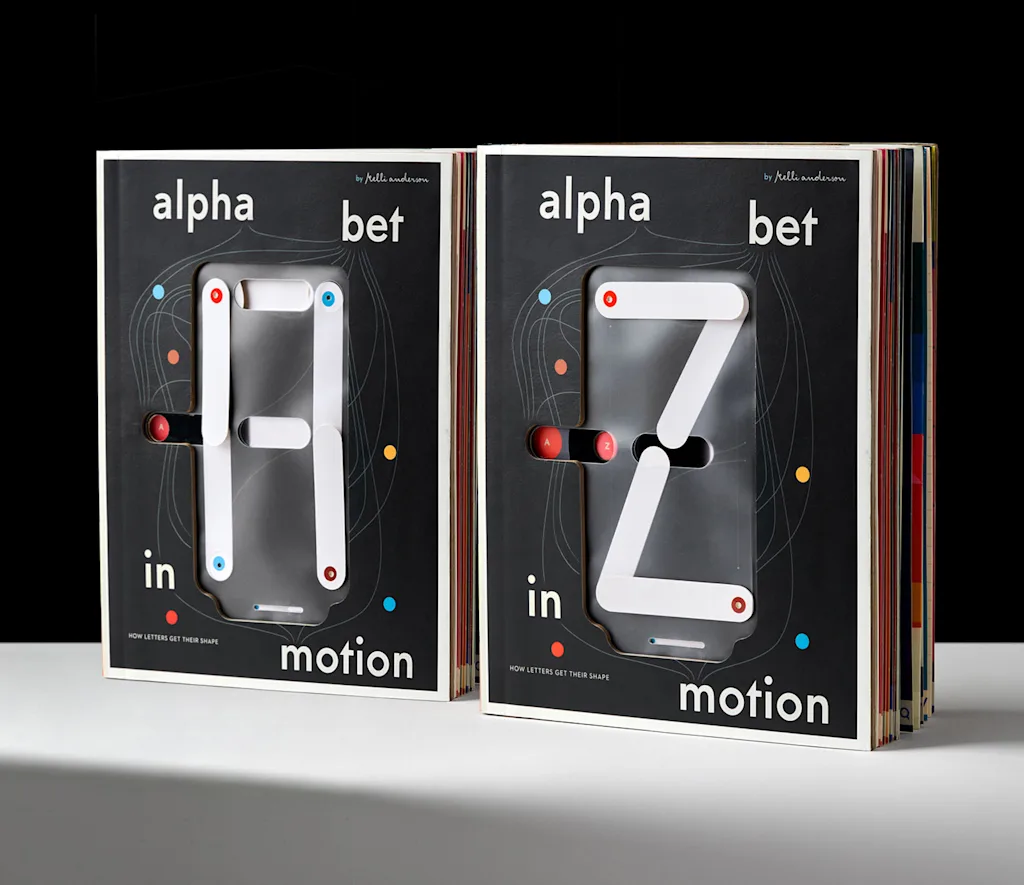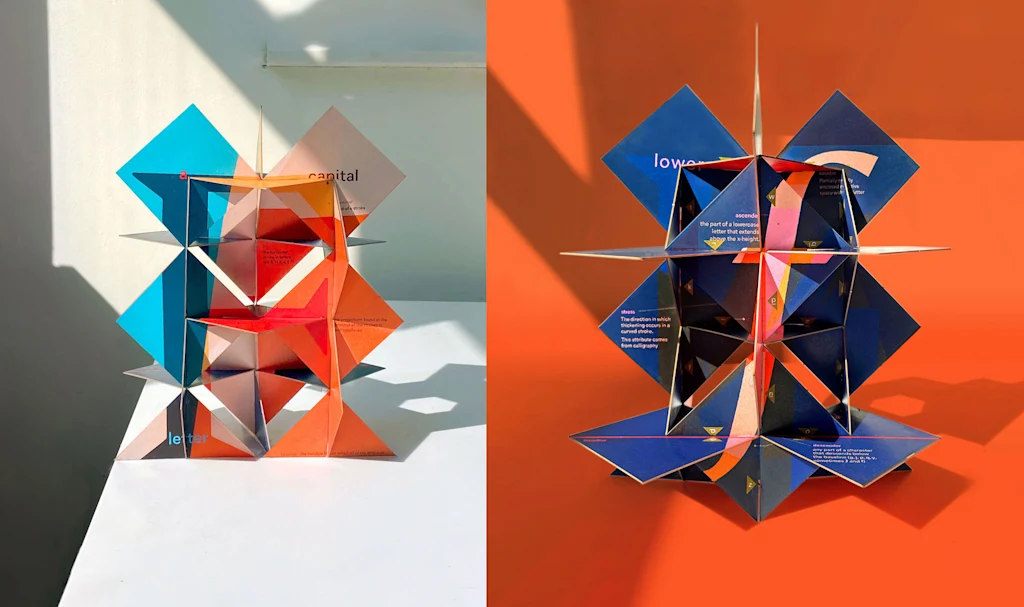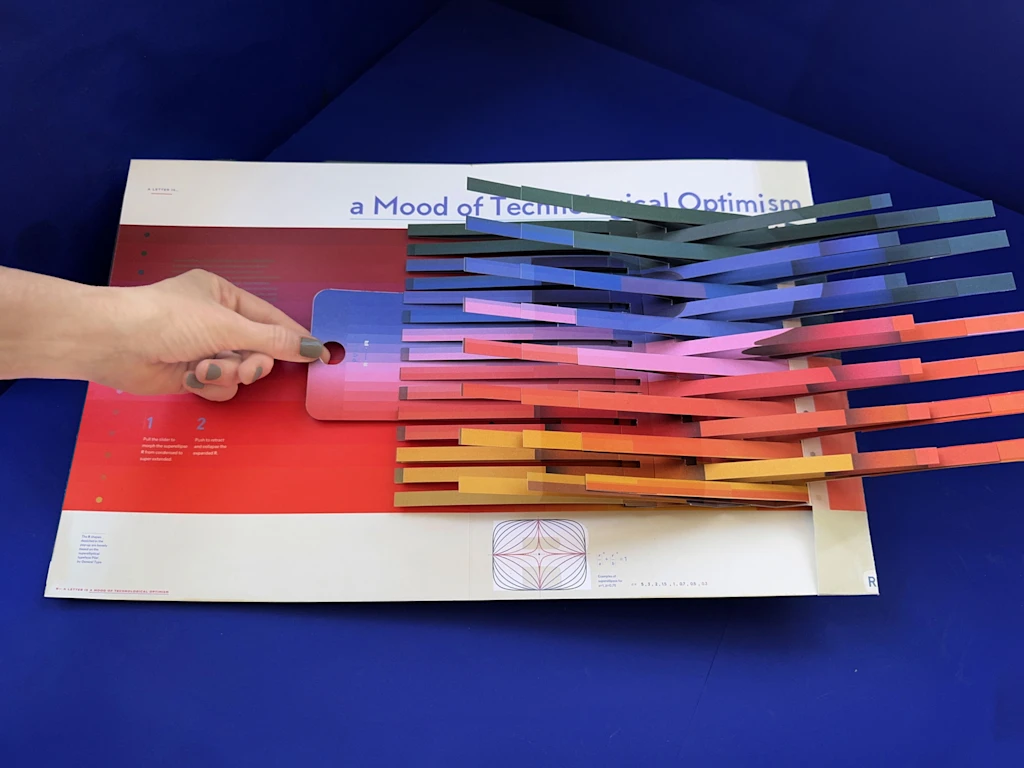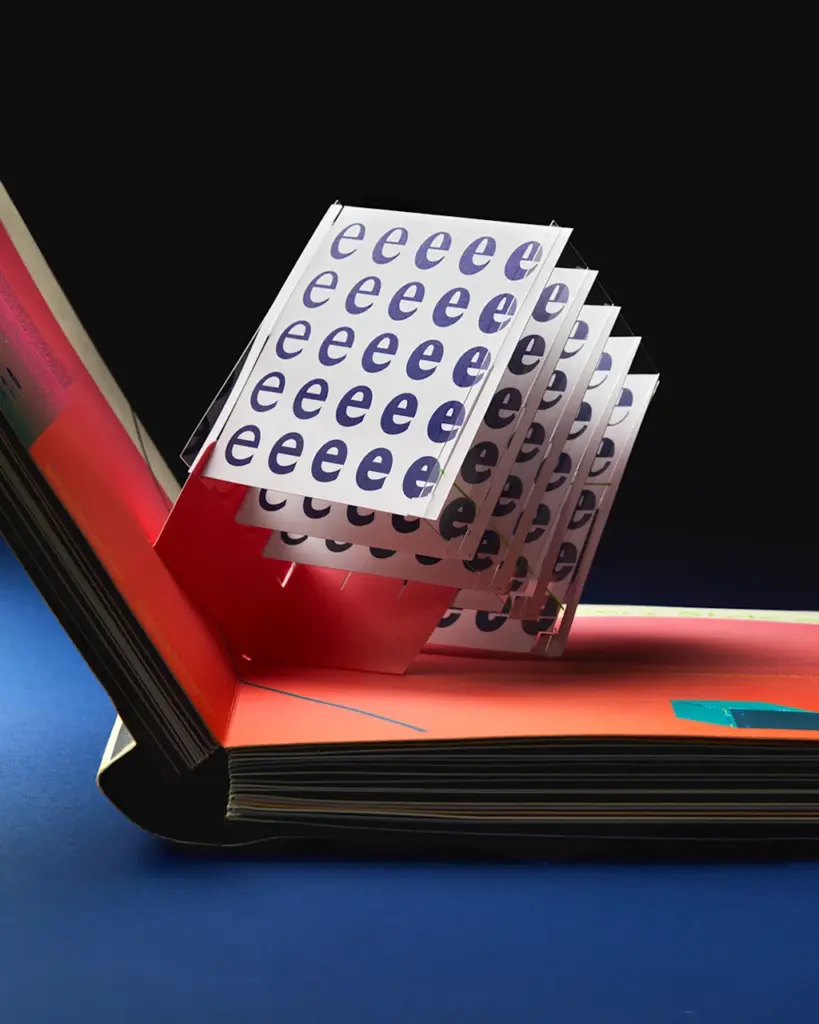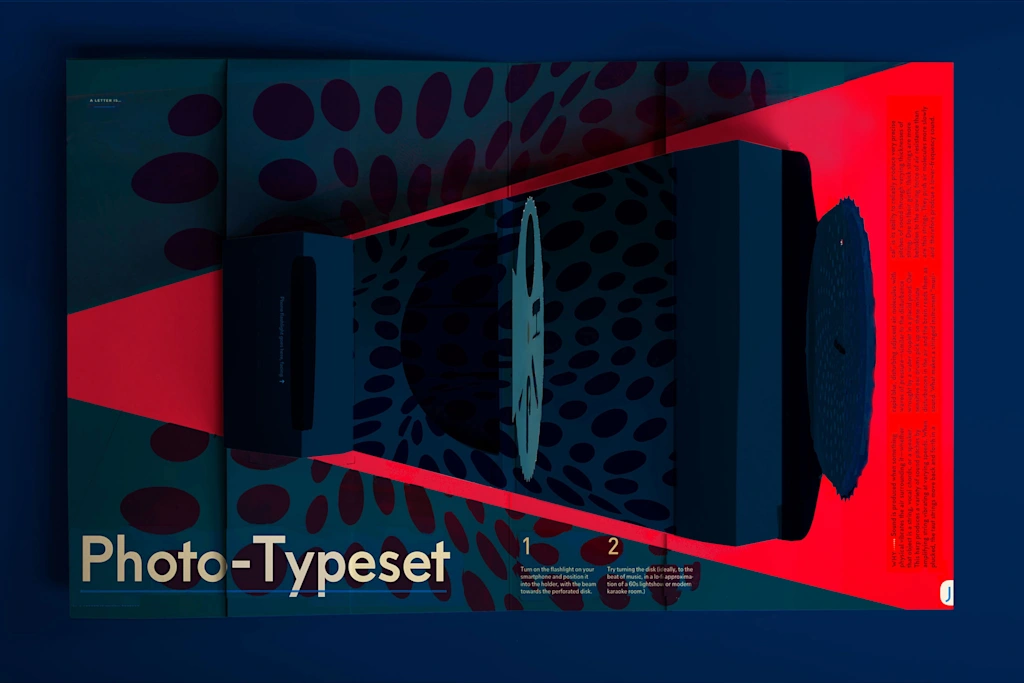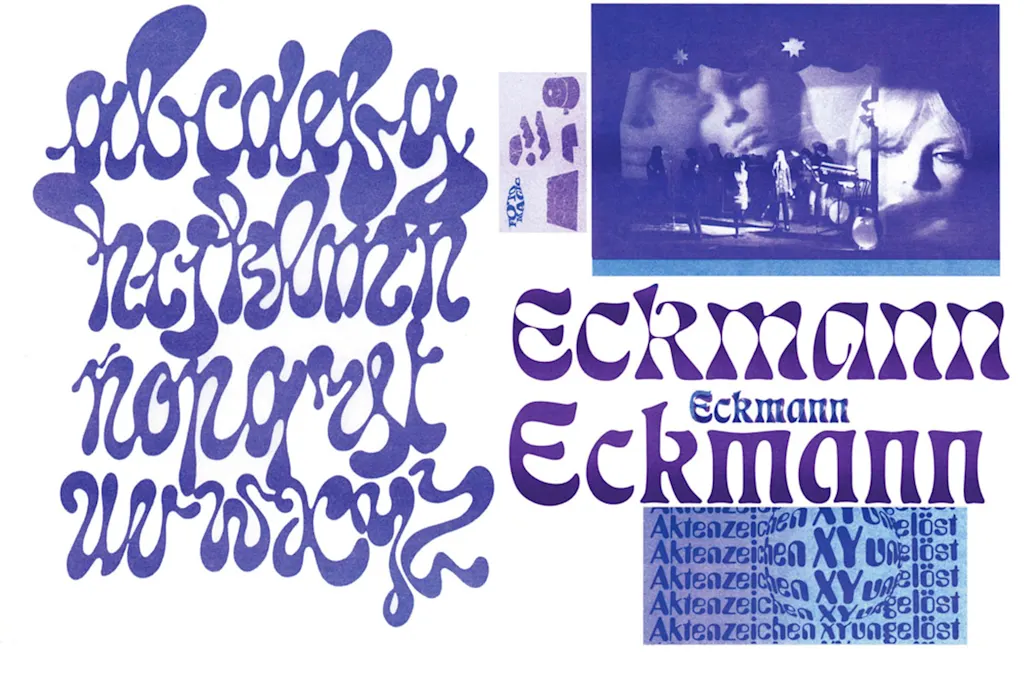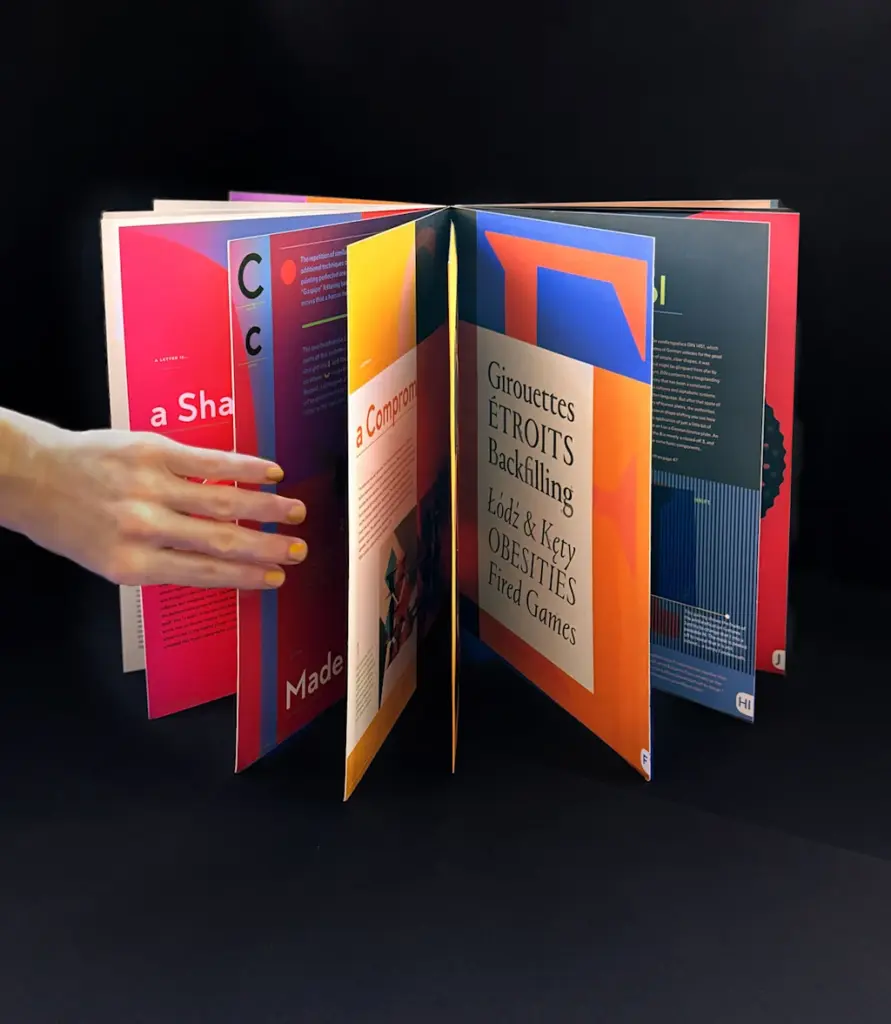
Neste livro, a história da tipografia salta das páginas – literalmente
A artista gráfica Kelli Anderson transforma a evolução das fontes em espetáculo de papel e luz
Você já se perguntou como a letra “A” ganhou a forma que tem? Ou por que algumas fontes automaticamente parecem “psicodélicas”? Ou de onde veio, afinal, a palavra “texto”?
Kelli Anderson, artista gráfica, autora e mestre em tudo o que envolve papel, já fez todas essas perguntas – e está respondendo cada uma delas em seu novo livro pop-up "Alphabet in Motion" ("Alfabeto em movimento", em tradução livre).
A obra leva o leitor por uma jornada interativa sobre a história da tipografia de A a Z, começando no Egito Antigo e chegando até a era digital.
Mas não se trata de uma obra histórica comum. Anderson criou à mão 17 mecanismos pop-up diferentes – de projeções de luz a sliders coloridos e ilusões surpreendentes – que mostram como a humanidade desenvolveu, com muito esforço, as tecnologias tipográficas ao longo do tempo.
Seu último livro pop-up, "This Book is a Camera" (Este livro é uma câmera", em tradução livre), foi lançado em 2015. Desde então, ela vinha sonhando com um novo conceito. A ideia só ganhou vida em 2019, quando começou a pesquisar a história da tipografia e o ofício por trás dela – e tudo fez sentido.
“Vivemos em uma realidade tipográfica na qual as letras nos fazem sentir coisas. Oferecer algum tipo de explicação satisfatória ajuda a dar mais significado ao porquê sentimos isso”, diz Anderson.
“Quando você vê aquelas letras psicodélicas e arredondadas, por que isso te lembra os anos 1960, Andy Warhol e a cultura underground? Quando você vê letras com aquele estilo mod, por que isso remete à era da corrida espacial?”
A artista mergulhou em coleções históricas de tipos na St. Bride Foundation, em Londres, além de livros e artigos acadêmicos. Aos poucos, construiu uma parede inteira (presa com fita crepe) repleta de exemplos que descobria.
Ao mesmo tempo, passou milhares de horas experimentando mecanismos pop-up em papel para demonstrar cada conceito. “Havia mecanismos que eu pensava: ‘isso é incrível! Preciso incluir só pelo espetáculo’”, conta Anderson.
“Mas então eu precisava encontrar um lugar onde aquilo fizesse sentido, onde realmente ajudasse a explicar uma ideia. Porque eu não queria colocar qualquer coisa apenas por diversão. Queria que, quando lessem o texto, as pessoas entendessem: ‘ah, isso demonstra uma tecnologia tipográfica específica desta época.’”
COMO AS FONTES PSICODÉLICAS GANHARAM FORMA
Um dos períodos que mais fascinaram Anderson foi o início dos anos 1960, explorado com profundidade no capítulo dedicado à letra “J”.
Ela queria entender por que a tipografia daquele período produziu tantas letras arredondadas, volumosas e até com formatos em chamas. Na pesquisa, descobriu que esses ícones estilísticos surgiram graças a uma nova tecnologia chamada fotocomposição.
A fotocomposição permitia que designers projetassem luz através de filmes e a organizassem em papel fotográfico, como em um layout de revista. O avanço tornou o processo muito mais rápido, barato e simples, substituindo métodos anteriores que envolviam… chumbo derretido.
No livro, o leitor pode vivenciar um pouco desse processo. Na página dedicada à letra “J”, um recorte de papel se transforma em um projetor para o iPhone: basta acender a lanterna e criar seu show tipográfico ao estilo dos anos 1960.
livro em 3D sobre tipografia
Crédito: Kelli Anderson
Essa é apenas uma das maneiras como o livro usa experiências táteis para contextualizar inovações tipográficas.
Entre outras páginas, há um modelo 3D que explica o surgimento de maiúsculas e minúsculas no Império Romano e na Idade Média; um mini pop-up sobre as primeiras fontes bitmap de videogames; e uma página interativa que mostra como a prática antiga da tecelagem moldou o alfabeto moderno e deu origem ao próprio termo “texto”.
livro em 3D sobre tipografia
Crédito: Kelli Anderson
Para Anderson, o grande objetivo deste projeto de seis anos é apresentar o mundo do design tipográfico a uma nova geração. “Espero que algumas pessoas comprem o livro para seus filhos pequenos, pensando que é apenas um livro pop-up do alfabeto, e o apreciem nesse nível”, diz Anderson.
“Depois, que o coloquem de volta na prateleira e, daqui a 12 anos, seus filhos o abram novamente e percebam que o design e a tipografia são interessantes, que não são algo isolado mas se conectam com o mundo e a cultura em geral”